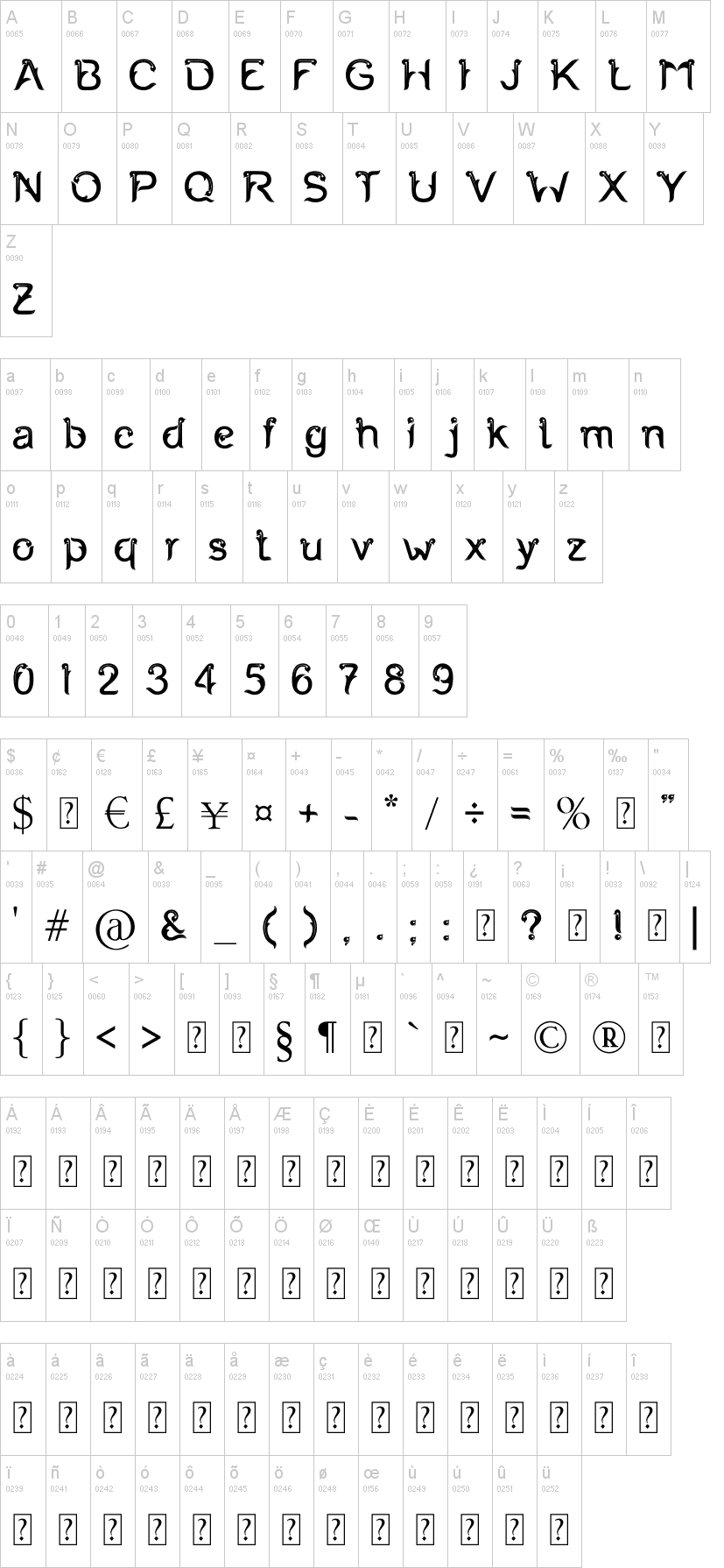
Note of the authorTypeface yang terinspirasi dari motif ragam hias budaya tradisi Minangkabau Kaluak Paku dari Sumatera Barat (West Sumatera) Indonesia.